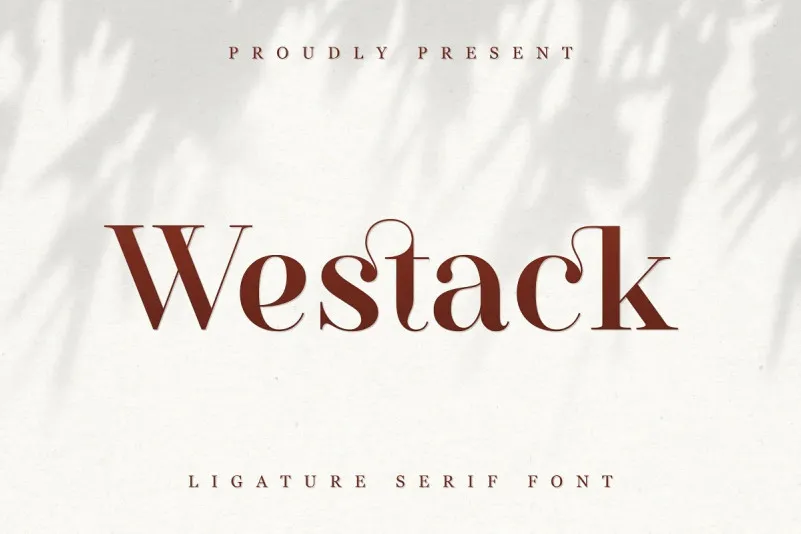
Westack Font – Fonte Grátis
Westack Font
A Westack Font é uma elegante tipografia séria que destaca-se pela sua ligatura fluida para conectar letras com suavidade e graça. Desenvolvida pelo designer Almarkha Type, essa fonte inspirou-se nas lembranças minimalistas de um logotipo famoso, tornando-a perfeita para criar templates, brochuras, vídeos, marcas publicitárias, logos e muito mais. Seu design harmonioso não apenas valoriza a simplicidade dos logos inspiradores, mas também oferece uma versão sofisticada que certamente se destaca em qualquer projeto de design. Este é um recurso visual elegante para designers e criativos que buscam um equilíbrio entre modernidade e sofisticação no seu trabalho gráfico.